Desde la noche de los tiempos, el lenguaje escrito ha sido determinante en la evolución de la especie humana, así como en la difusión y preservación del conocimiento y la historia. Desde los textos grabados en piedra, el papiro y los monumentos romanos, hasta la Biblia de Gutenberg y el universo digital actual, nada ha podido sustituir el papel de la tipografía.
Todos conocemos la frase: «Una imagen vale más que mil palabras». Sin embargo, un filósofo brasileño supo cuestionarla con humor: «Sí, ¡pero quiero ver eso expresado con una imagen!». Esta ironía resume con precisión el poder inmutable de la escritura.
El estudio de diseño argentino YaniGuille&Co se dedica principalmente al diseño tipográfico, el lettering, la ilustración y la caligrafía. Fundado y dirigido por Yani Arabena y Guille Vizzari (a.k.a. a.k.a. Yani&Guille), en 2021 incorporaron a Agustín Pizarro Maire como director de arte e ilustrador. Con base en la ciudad de Buenos Aires, sus creaciones trascienden la forma tipográfica para definir con claridad la personalidad y el carácter de sus clientes y colaboradores.
“La producción de nuestro estudio gira en torno a la ilustración, la caligrafía y el diseño tipográfico. Las tres disciplinas son fundamentales para nosotros, y podría decirse que cada uno de nosotros tres representa una de ellas. El diseño tipográfico, en particular, tiene la capacidad de transmitir no solo un mensaje literal, sino también un conjunto de ideas y sensaciones. Puede construir, por ejemplo, un logotipo, ese componente simbólico e identitario que da carácter a una marca, o bien completar la construcción de una identidad visual. Un sistema tipográfico puede generar un tono de voz, la forma visual del sonido hablado de una marca y, con suerte, perdurar en el tiempo hasta formar parte de una cultura determinada. Esa dualidad entre texto e imagen que nos ofrece la tipografía nos conmueve profundamente. Nos nace desde adentro y no podemos evitar volcarla en cada oportunidad.”
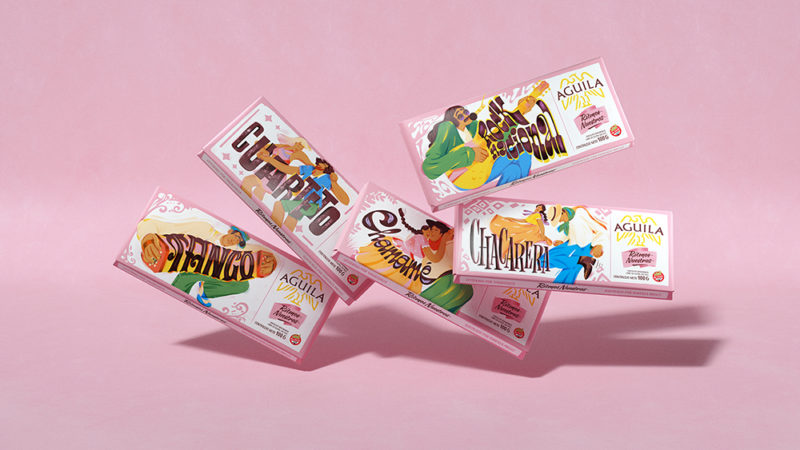
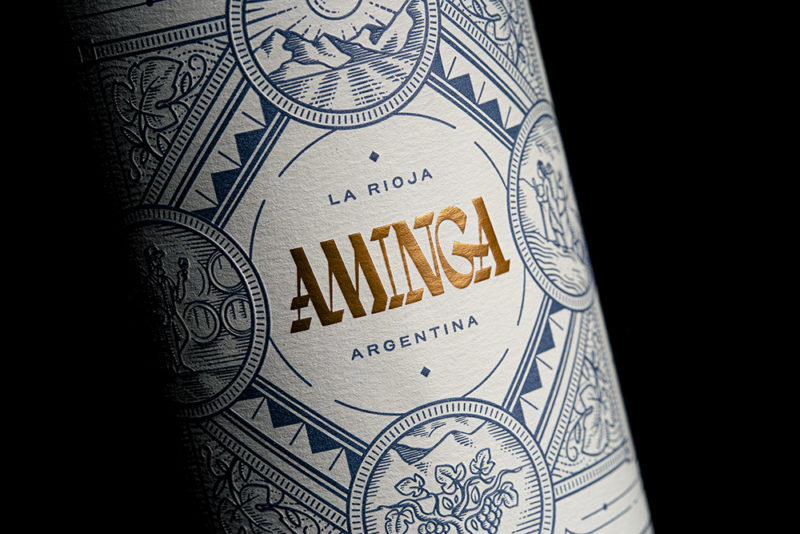
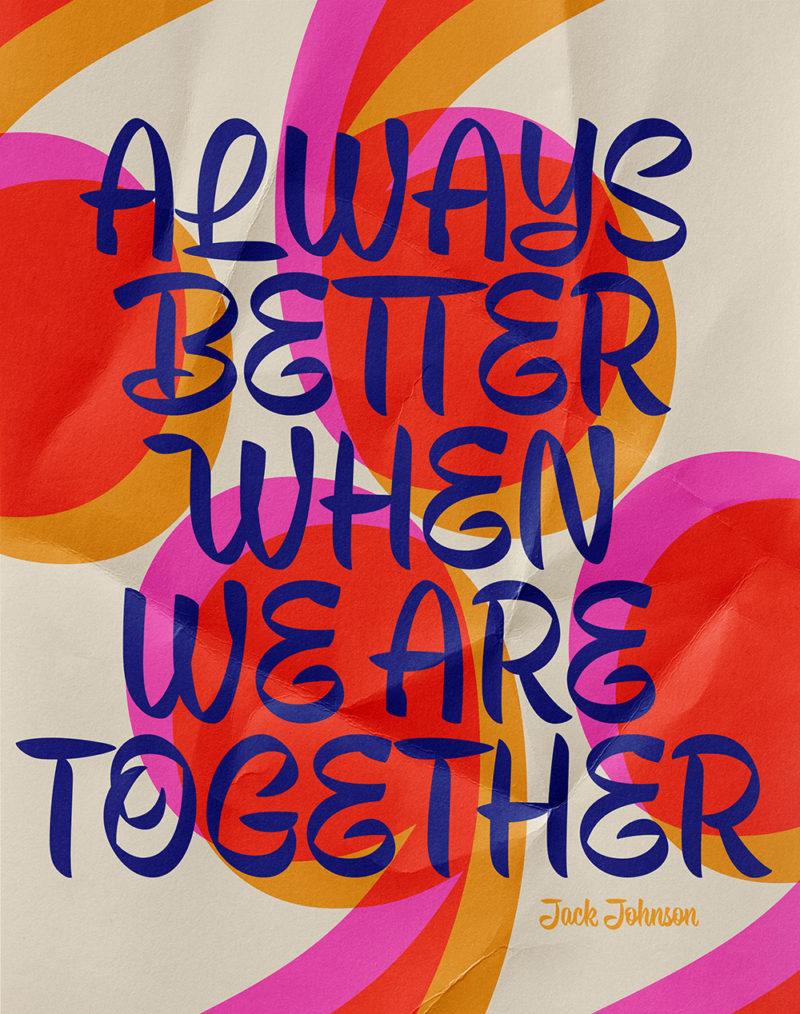
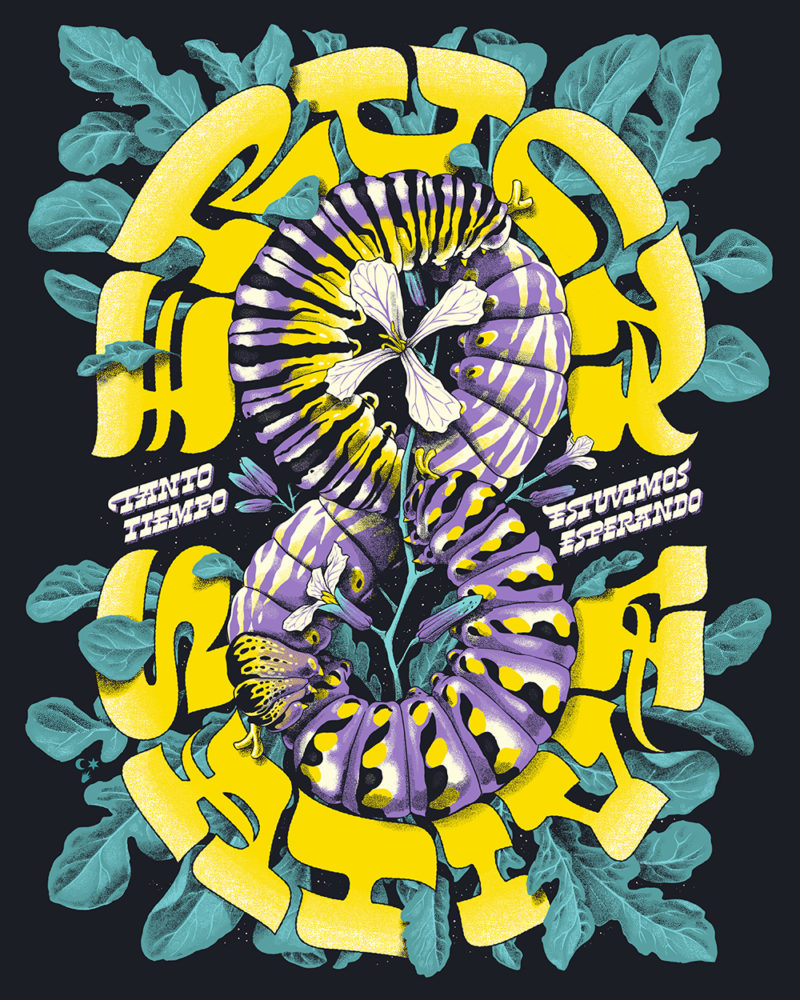
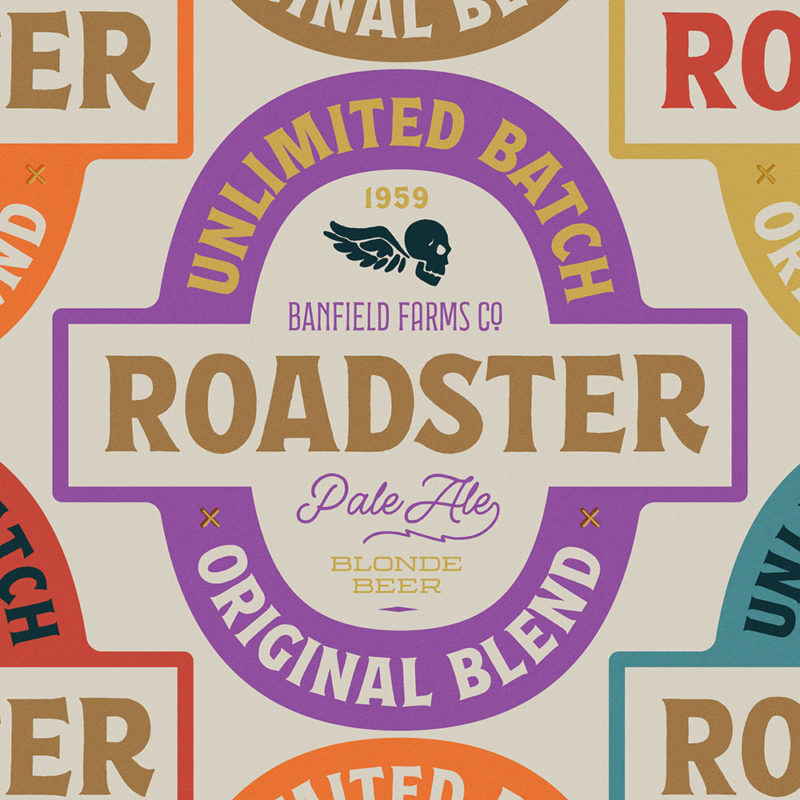
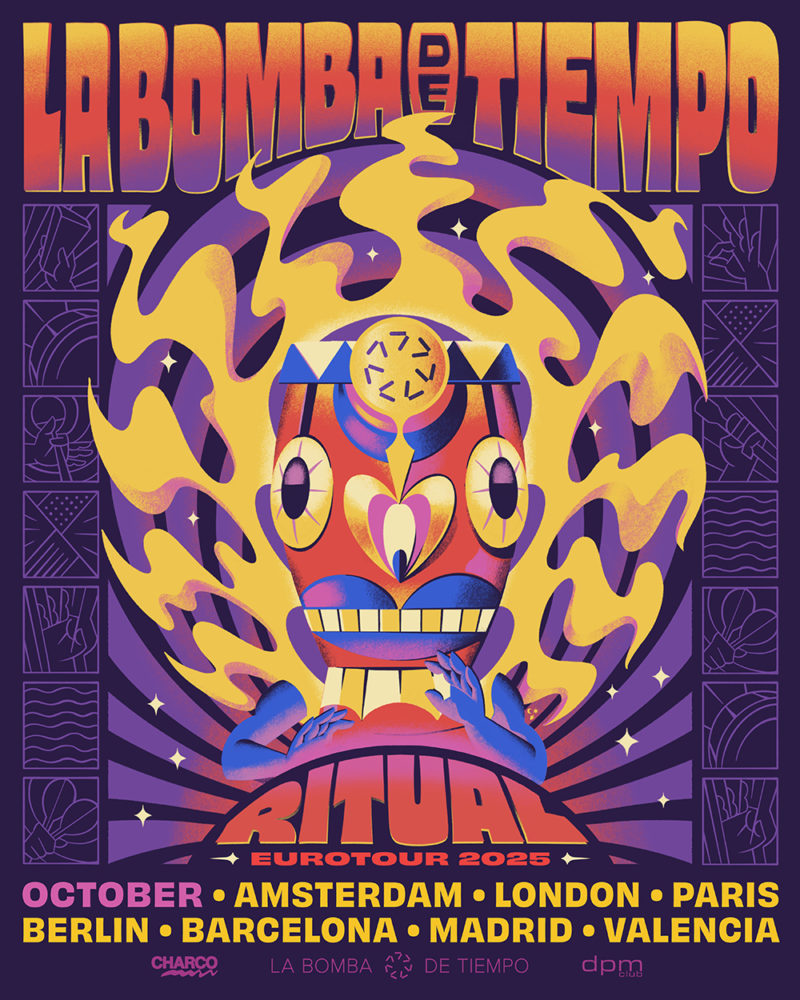
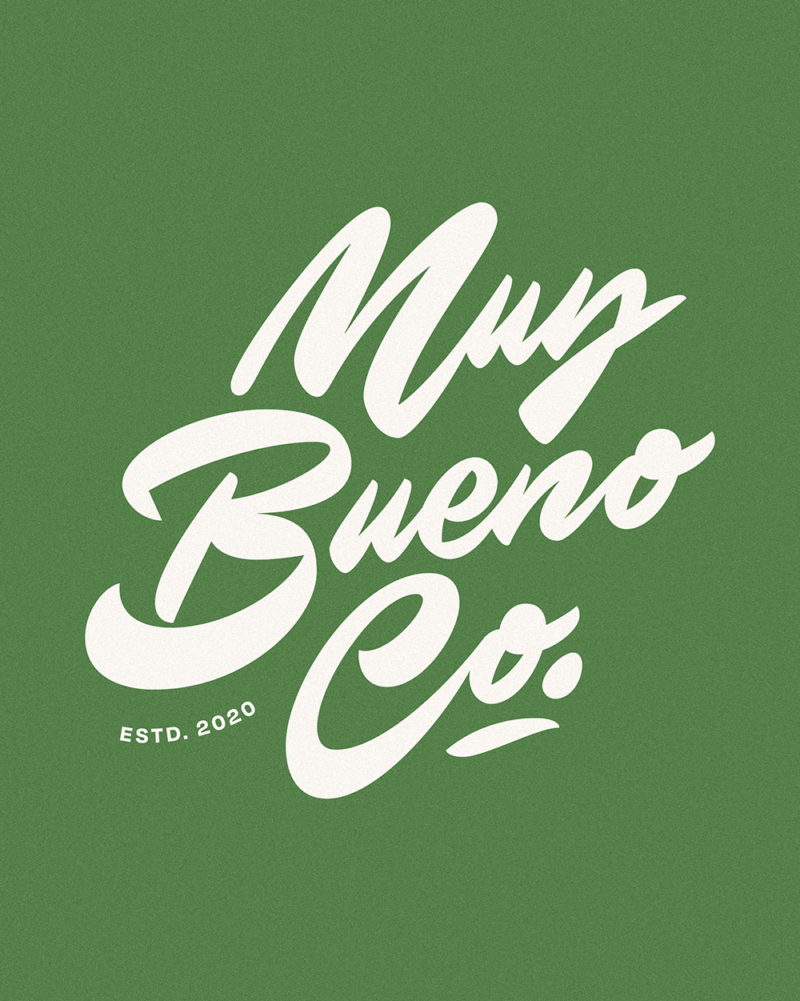
Observar su trabajo es reconocer un profundo conocimiento de la tipografía, articulado con un enfoque riguroso de experimentación que da lugar a proyectos notables. Así explican su proceso creativo:
“Siempre comenzamos con papel y lápiz. Tanto para pensar ideas como para empezar a bocetarlas. En el estudio, cada uno de nosotros tiene cuadernos por todas partes, llenos de bocetos, anotaciones e ideas. De todas ellas, solo unas pocas llegan a buen puerto (el resto se transforma en combustible para seguir avanzando). A partir de esos primeros bocetos e ideas, trabajamos en equipo: hablamos y compartimos lo que pensamos, lo que nos genera la idea o el boceto del otro, y así la propuesta empieza a tomar una forma propia, en la que prevalece la idea inicial de su autor y pasa a ser una idea de equipo. Esto, por un lado, permite que las ideas maduren rápidamente, y por otro, nos obliga a dejar el ego fuera del proceso. Luego, ya con la aprobación de la idea y el boceto, en la etapa de producción analizamos qué manos atacan qué parte del proyecto, o mismo si es preciso colaborar con más personas con otro expertise. No es lo mismo si se trata de una única pieza como un póster, o si hay que desarrollar un sistema de branding con cierta profundidad. Sea cual sea la escala, el proceso siempre es el más importante.”
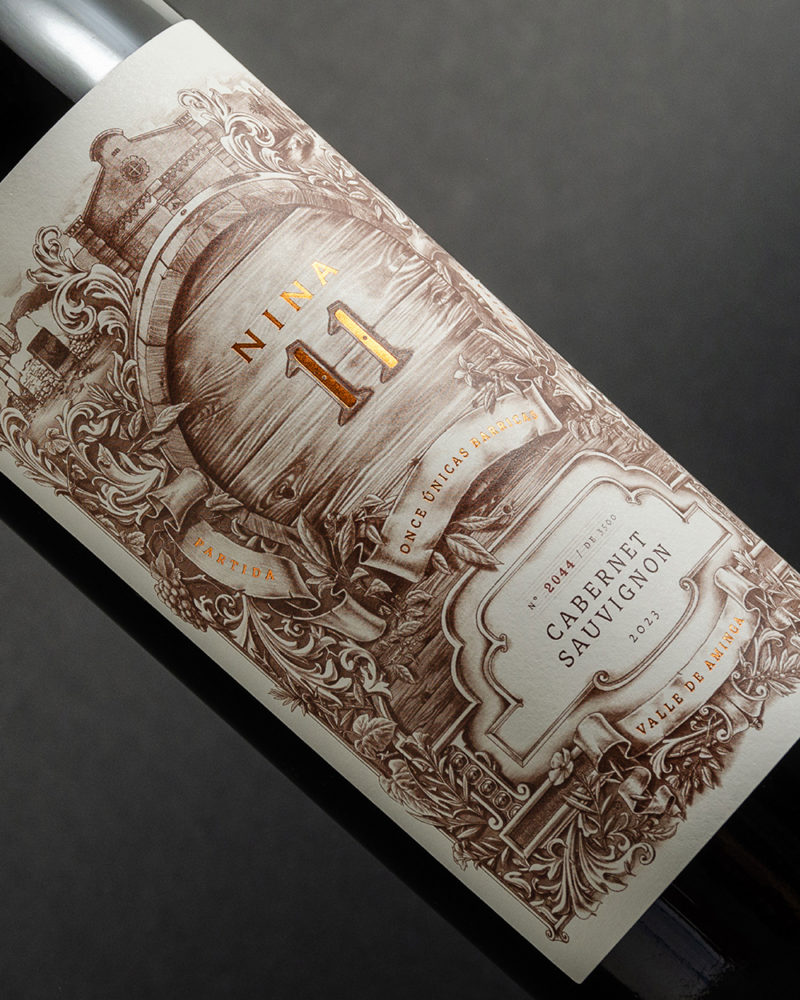
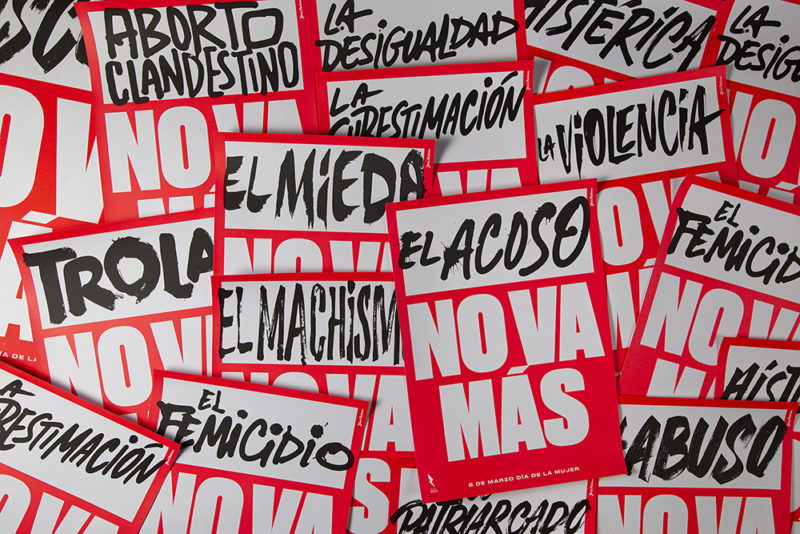
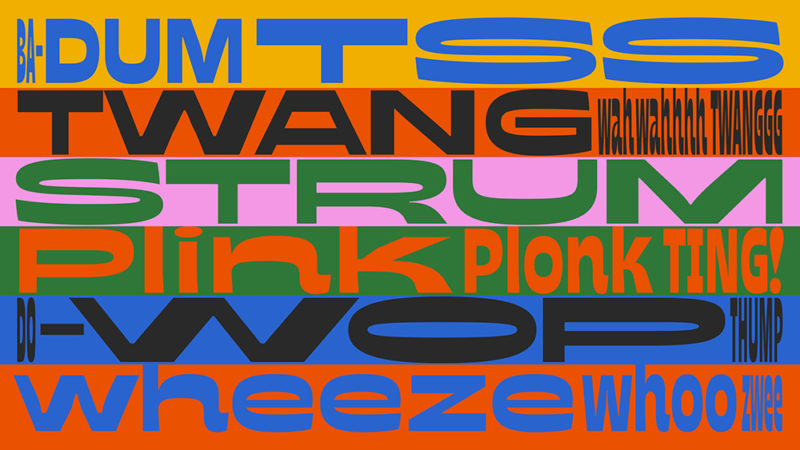
Como estudio conformado por jóvenes diseñadores, su relación con la actual sobreexposición visual y su forma de abordar el desafío de destacar en medio del ruido digital es clara:
“Sin dudas las nuevas generaciones tienen un gran trabajo al tener que lidiar con esta sobreexposición, y sobre todo a la inmediatez. Por un lado las redes sociales y los portales como Behance permiten llegar a grandes audiencias y hacer que nuestro trabajo circule. Un costado negativo de estos mecanismos es que es inevitable la comparación con el otro, pero esa comparación siempre es carente de argumentos. Nuestra postura es tratar de dejar de lado ese costado negativo, siempre enfocándonos en lo que a nosotros nos interesa. Qué inquietudes o búsquedas tenemos al momento de encarar un nuevo desafío? Si podemos volcarlas en cada proyecto, es algo que indudablemente nos motiva y nos empuja para buscar superarnos”
Respecto al futuro de la profesión —y del propio estudio— son contundentes:
“Desde nuestros comienzos estamos en movimiento. No nos anclamos en estilos ni en modas pasajeras: buscamos ser fieles a nuestras inquietudes. Sin dudas las nuevas tecnologías moldean las disciplinas en las que nos enmarcamos y nos obligan a adaptarnos a nuevas formas de pensamiento, pero nuestra intención fue —y será siempre— mantener la esencia, aquello que nos hace únicos.”